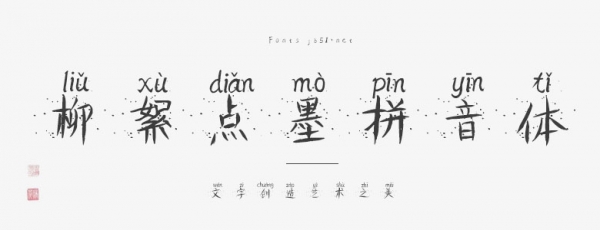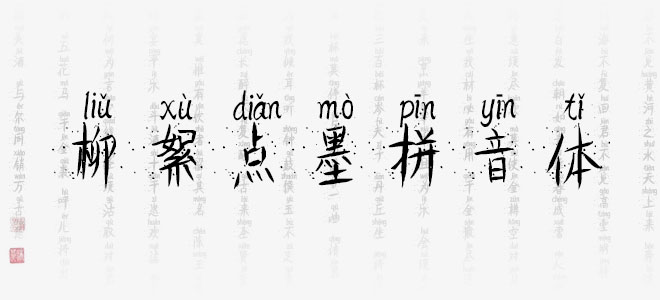
柳絮點(diǎn)墨拼音體是一款賞心悅目的藝術(shù)字體,自帶拼音標(biāo)注效果,具有強(qiáng)烈的視覺沖擊力。適用于海報(bào)、電商海報(bào)設(shè)計(jì)、店鋪設(shè)計(jì)、標(biāo)志設(shè)計(jì)、字體設(shè)計(jì)等領(lǐng)域。
柳絮點(diǎn)墨拼音體